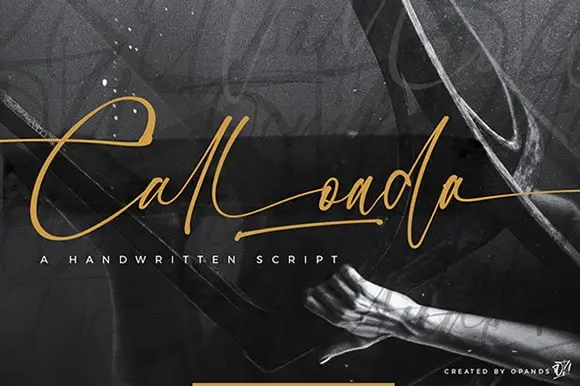
Calloada Script Font
A Calloada Script Font é uma escolha para quem busca uma fonte que abraça a essência das experiências únicas e passageiras do cotidiano. Inspirada no realismo mágico, essa fonte escrita à mão captura o instante fugaz de momentos especiais ou simplesmente memoráveis. Os designers Opand criaram Calloada Script para destacar os sentimentos que esses instantes provocam. Algumas das letras podem ser quase ilegíveis, mas é justamente isso o que torna essa fonte única. Suas formas têm a capacidade de despertar emoções e transmitir um sentimento único – talvez até mesmo uma mistura de nostalgia e esperança em cada letra. Essa propriedade da Calloada Script Font está diretamente relacionada à ideia original do designer: nos momentos em que a emoção é mais importante, nossa mente pode decifrar as formas das letras. Em um mundo onde muitas vezes nossos sentimentos são apagados e esquecidos pelo ritmo acelerado dos tempos modernos, Calloada Script é uma paixão para celebrar esses instantes. Ela é perfeita para designers que buscam adicionar um toque especial a seus trabalhos de arte digital, destacando os momentos singulares em suas criações. É uma fonte que fala mais alto com o coração do que as letras escritas, e é isso o que torna Calloada Script uma escolha única e emocionante para qualquer projeto visual.